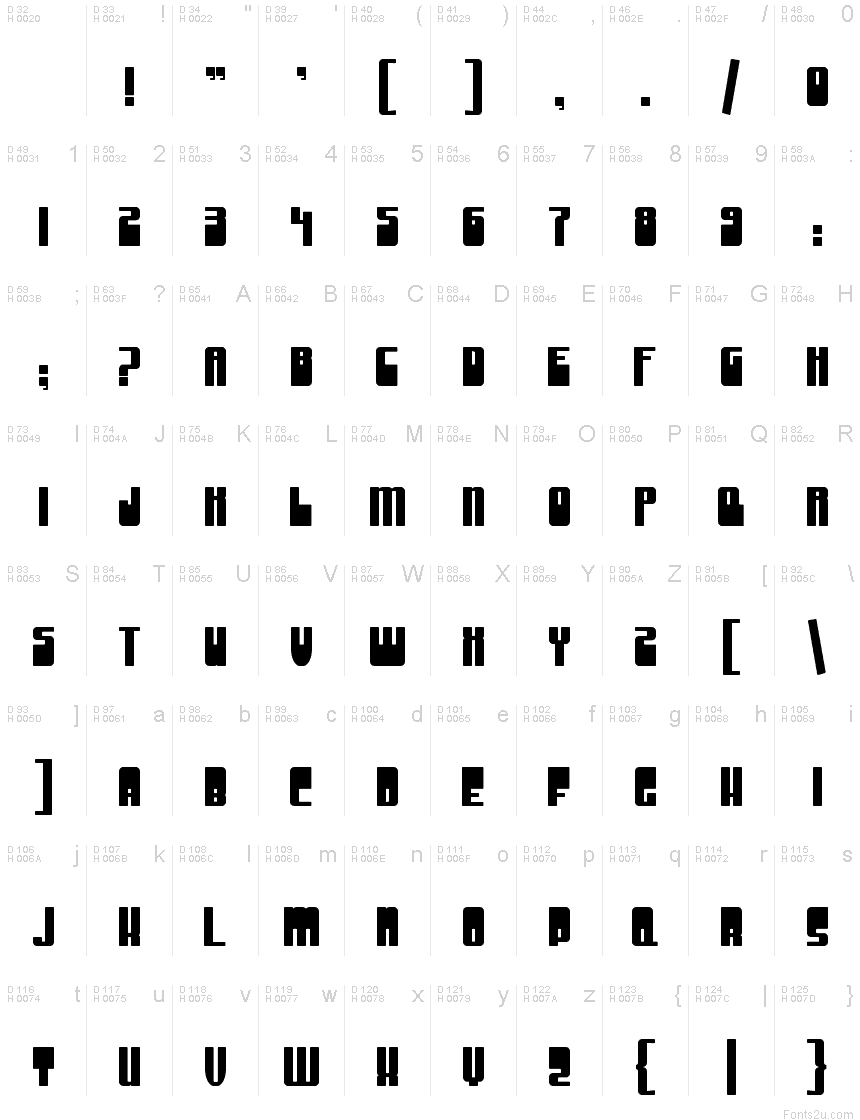
Groove Machine Upright od Shywedge to darmowy, groovowy krój displayowy, który wygląda, jakby został wyrzeźbiony w winylu. Ciężkie, pionowe litery o kwadratowych krawędziach i gładkich, zaokrąglonych kształtach nadają mu wyrazisty charakter, idealny na plakaty klubowe. Zwarty rytm każdego słowa przypomina automat perkusyjny idealnie trzymający tempo. Krój wnosi retro-futurystyczną energię, która jest jednocześnie zabawna i imponująca – idealna, gdy chcesz, by nagłówek uderzył jak mocny bas.
Dzięki Groove Machine Upright nagłówki nie tylko widnieją na stronie – one pulsują. Ten darmowy font świetnie sprawdza się na ulotkach muzycznych, w brandingu rave’ów i festiwali, logotypach DJ-skich, okładkach gier retro, grafikach streamingowych i na odważnych nadrukach. Stosuj go w dużym formacie, aby uzyskać maksymalny efekt, i zestaw z czystym, geometrycznym krojem bezszeryfowym w tekście głównym, aby te masywne, żłobione kształty mogły błyszczeć w świetle reflektorów.